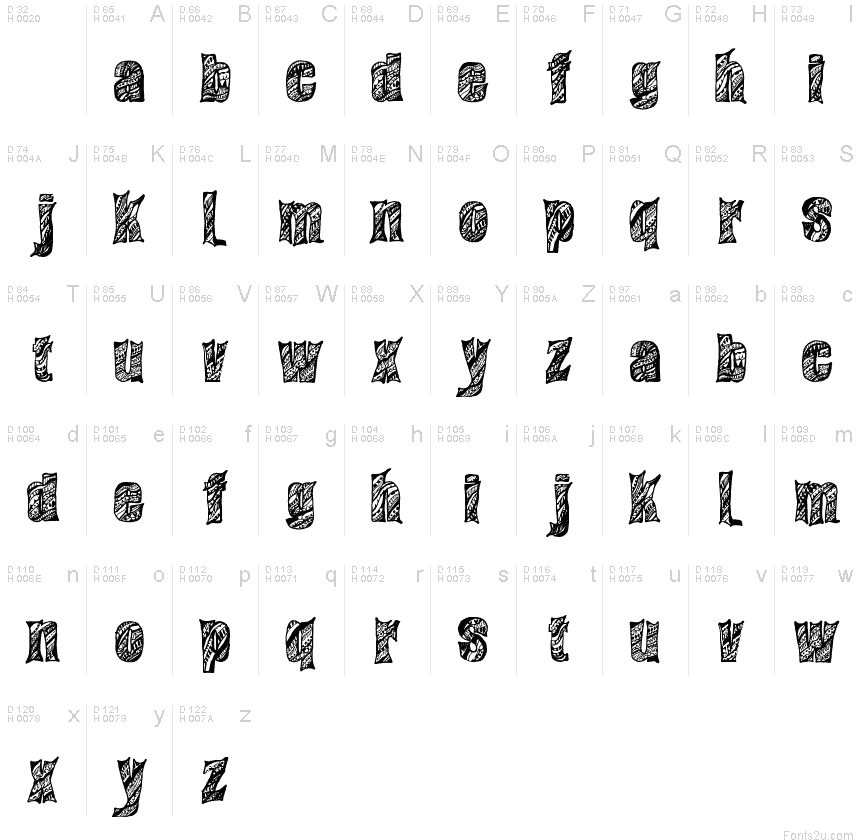
Sixties Regular
Sixties Regular di CloutierFontes è un font display psichedelico gratuito che richiama le atmosfere dei poster anni '60 disegnati a mano. Le lettere sono ondulate e teatrali: grazie ai contorni curvi e agli interni rigati e decorati, l'intero font sembra una scritta dipinta a mano piuttosto che una normale tipografia.
È l'ideale per copertine di album, poster di festival, packaging di boutique, branding di caffè retrò e titoli di riviste, dove un tocco di movimento nelle lettere aiuta a definire il tema. Essendo un font gratuito, è perfetto per titoli brevi, logotipi e cartelli, poiché la ricca decorazione interna dona anche a poche lettere l'aspetto di un'opera grafica completa.